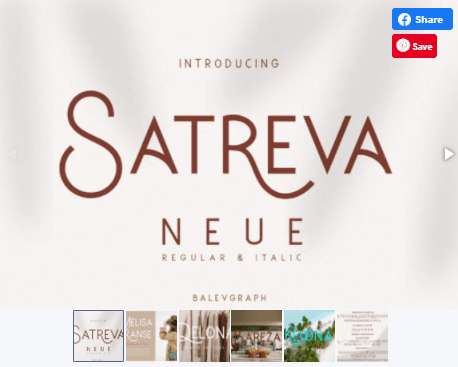
Satreva Neue Font
Satreva Neue - тонкий, элегантный и отчетливый шрифт без засечек. Благодаря своему лаконичному и простому стилю, подходящий для самых разных дизайнов, этот шрифт может стать вашим любимым шрифтом в любом случае!